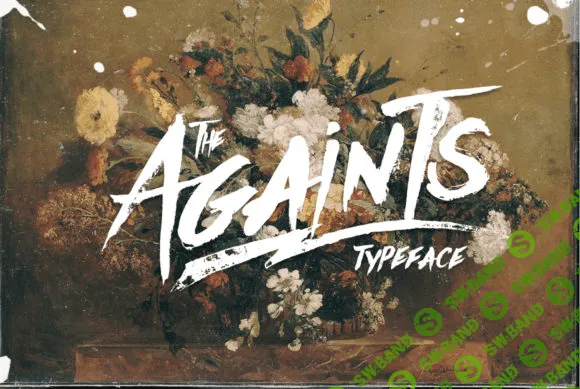
Название: The Againts Font
The Againts - это смелый, грубоватый текстурированный и аутентичный шрифт для отображения на дисплее.
Он подходит для создания различных дизайнов, требующих жуткого или жуткого ощущения.